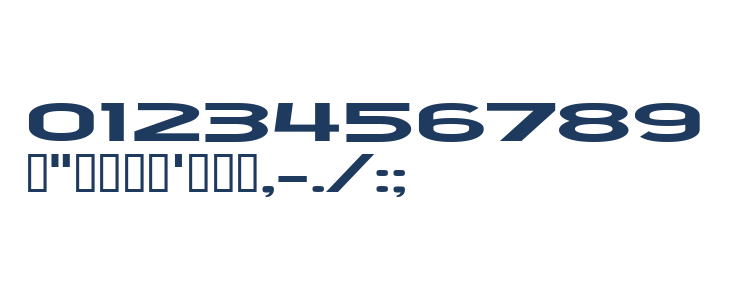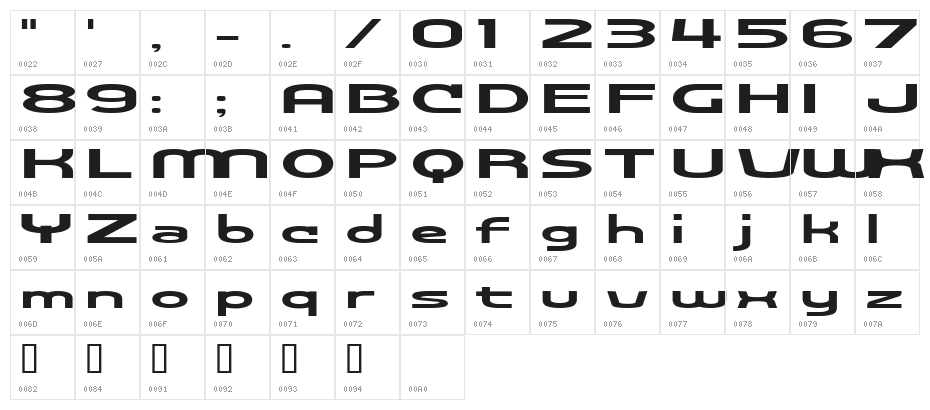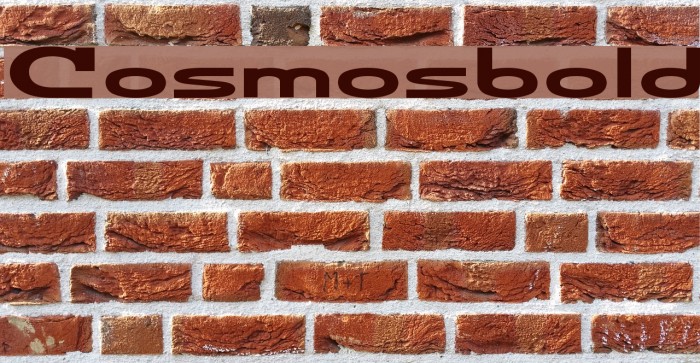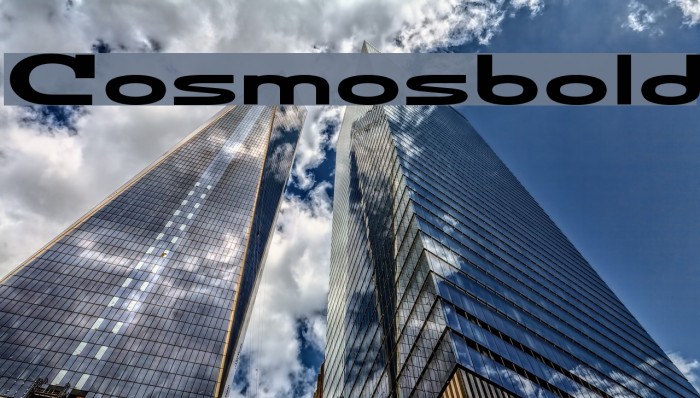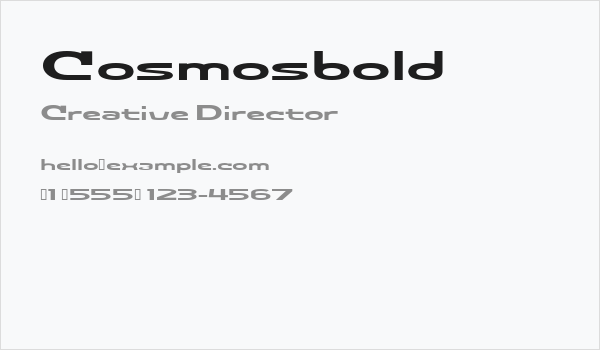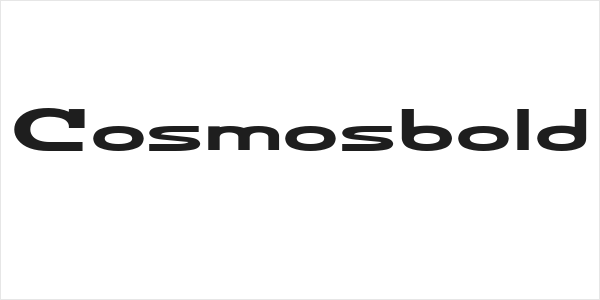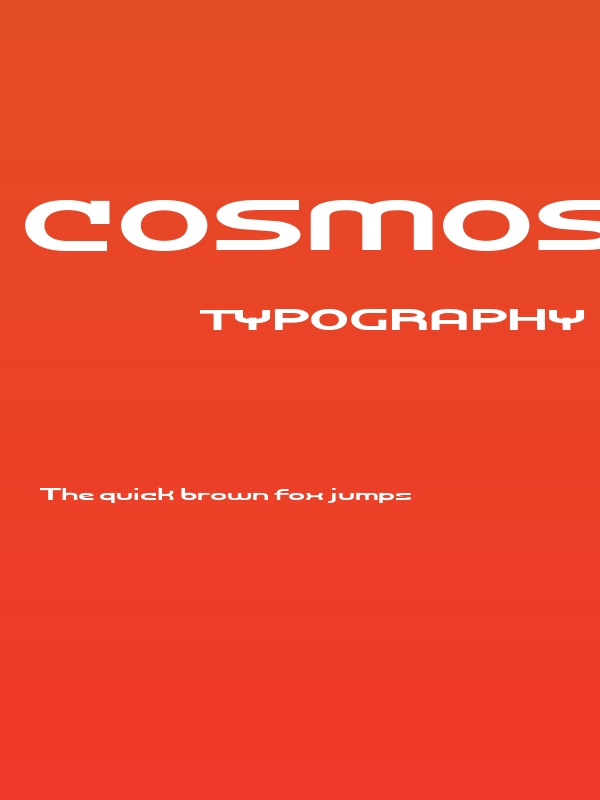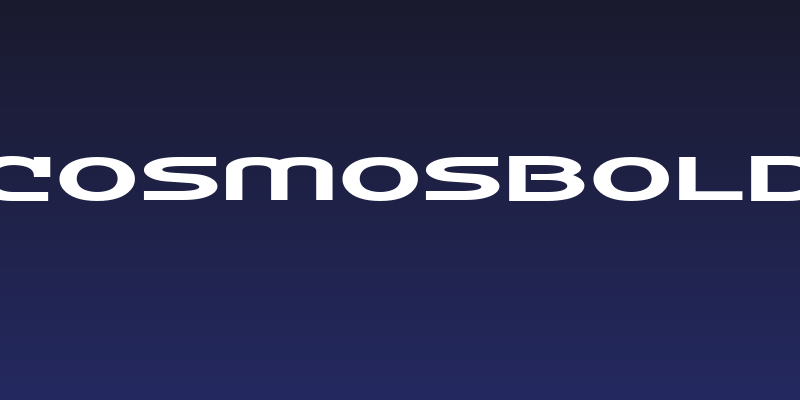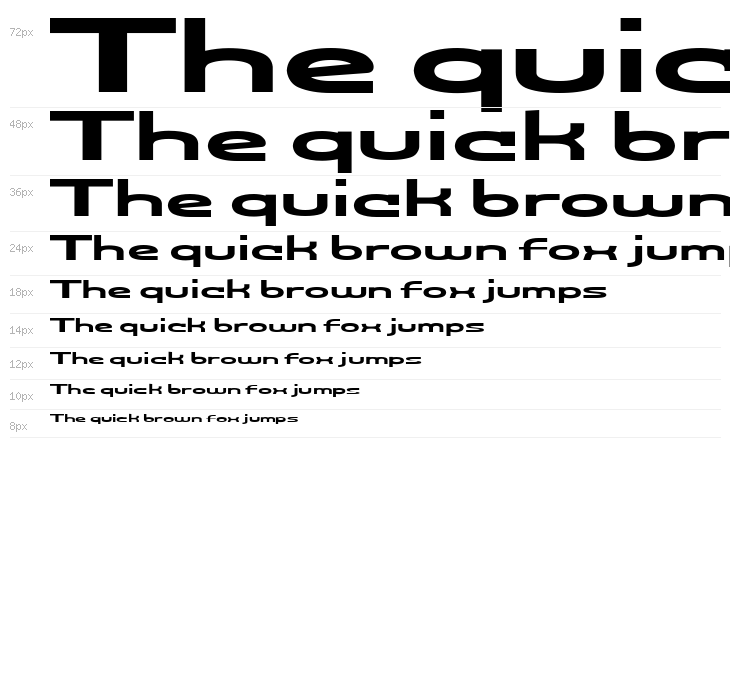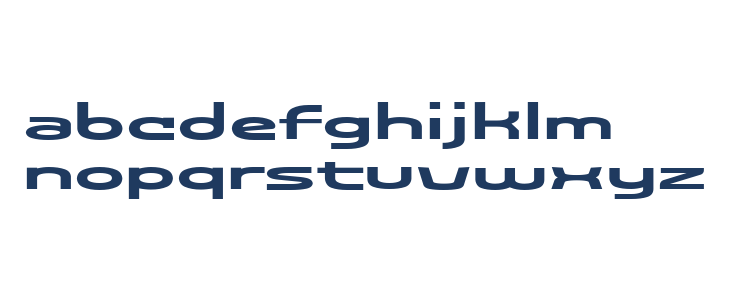
Cosmosbold Font
| Caso d'uso | Headlines, Logos, Digital Interfaces |
| Progetti proposti | Ideal for technology branding, sci-fi themed projects, modern advertising, and digital interfaces. |